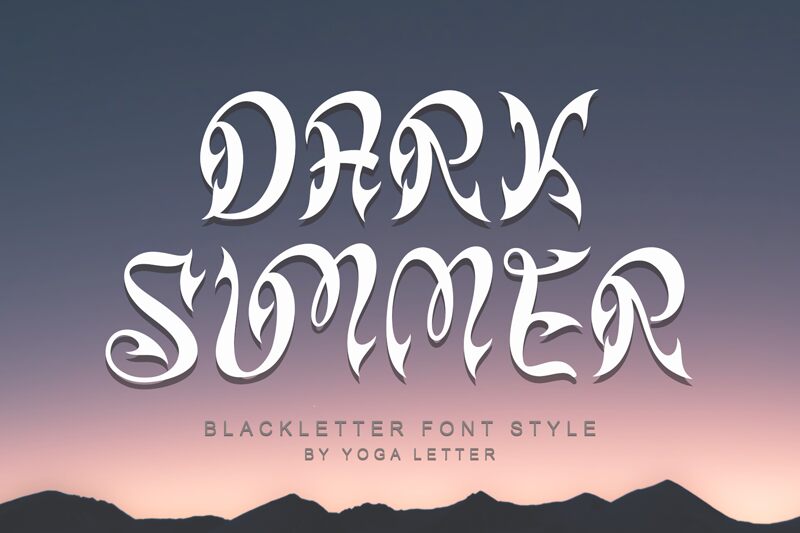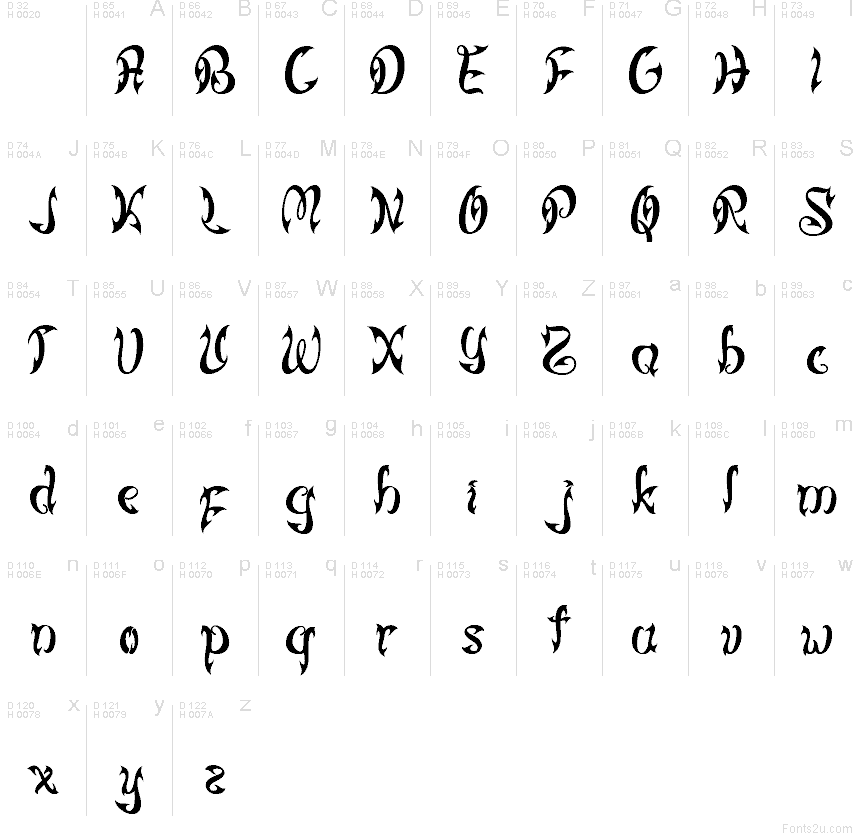
Dark Summer Demo
La police Dark Summer de Yoga Letter est une police gothique de type display, gratuite, caractérisée par des courbes calligraphiques fluides et des terminaisons acérées. Les lettres adoptent un rythme blackletter délié, tout en présentant des formes plus douces et ornementales que les styles gothiques historiques traditionnels.
Dark Summer est idéale pour les designs de tatouage, les pochettes d’albums, les titres de films d’horreur, les affiches, les logos et les visuels saisonniers nécessitant une touche manuscrite dramatique. Ses traits fluides et ses empattements marqués conviennent également aux invitations, aux graphismes pour réseaux sociaux, au merchandising et aux titres décoratifs où le lettrage lui-même apporte tout le caractère au visuel.